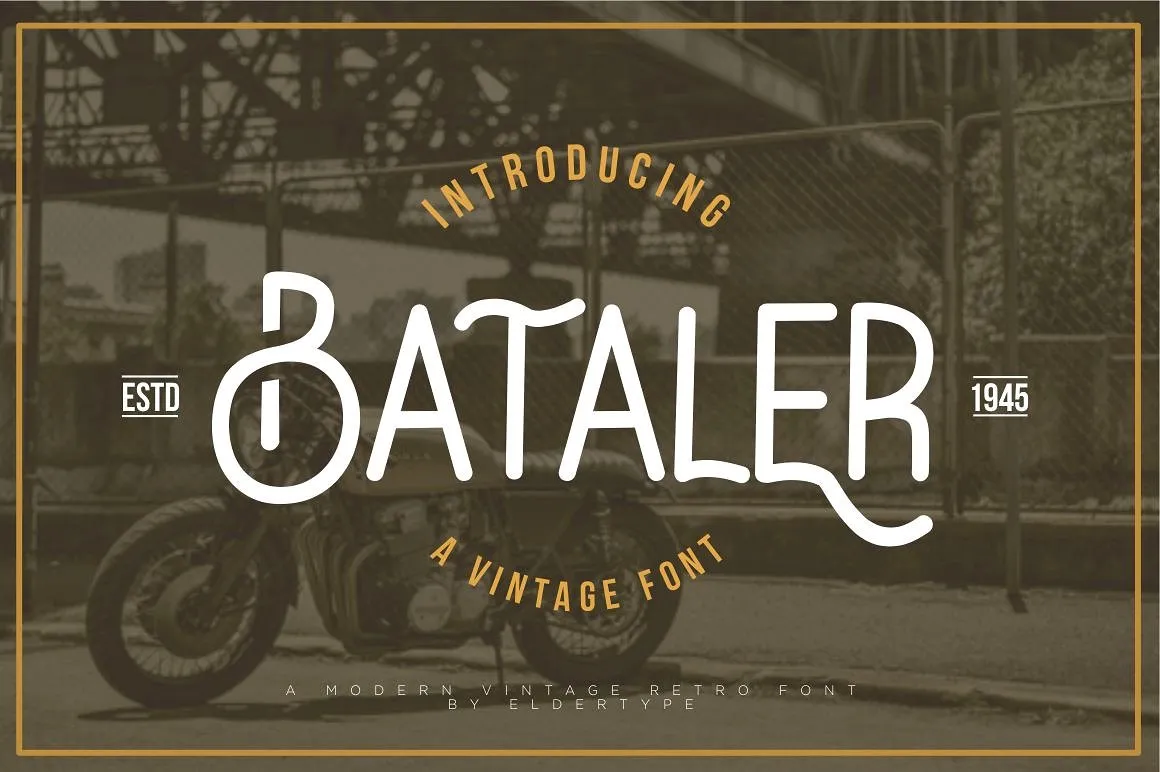
Bataler Typeface – Download Grátis
A Bataler Typeface é uma opção exuberante para os designers buscando elementos vintage retro no seu trabalho, sem dúvida alguma apropriada para aquelas obras que necessitam de um toque especial e encantador. Cria-se por Eldertype Studio, esta fonte vem em perfeita harmonia com o estilo de design moderno e elegante, oferecendo uma aparência profissional ideal para os projetos onde se deseja adicionar romantismo e charme. Idealmente utilizada como fontes visuais ou headlines, a Bataler Typeface é um ótimo complemento para criações em logotipos, logomarcas, marcas de marca, embalagens de produtos, capas de livros, estampas de camisetas e posts nas redes sociais. Esta fonte se encaixa perfeitamente com os ambientes que necessitam de uma conotação vintage sem perder seu caráter moderno. Com a Bataler Typeface, você pode recriar atmosferas nostálgicas em qualquer obra digital, mantendo um equilíbrio entre o clássico e a atualidade.